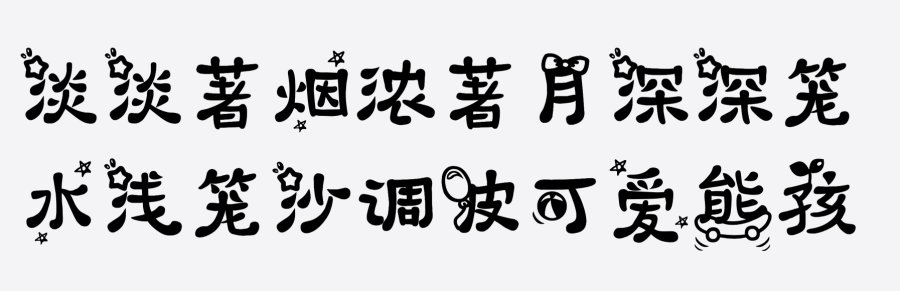
目前,母婴产品的种类越来越多,父母对孩子的细致照顾也是该行业对产品的需求不断增长,因此母婴行业在营销宣传中的投资比例也相应增加。
母婴行业的广告字体一般会选择更可爱的卡通字体,符合儿童产品的风格,同时会更亲和力,缩短与客户的距离。
义启熊孩子体是一款很好玩的字体,结合熊孩子的元素,将小星星、足球、蝴蝶结等元素很好的融合在一起,突出表现熊孩子的任性、调皮、爱玩的心理,充满童真,制作出来的字体创意十足,充满活力。